纪念天一阁建阁450周年,“芸香四溢———明代书籍文化的世界影响”今起在天一阁博物馆的云在楼开展,集中展出近50种有代表性的明代书籍,内容分为“线装书:古书的定型”、“宋体字:汉字的规范”和“明刻本:文本的共通”三部分,通过书籍的内容书写、实物制作、出版流通、收藏鉴赏等,多方面展示“明代书”的文化,其中不乏当前古文献学、书籍史和明代文化研究中的最新成果。展览将持续到2017年2月14日。
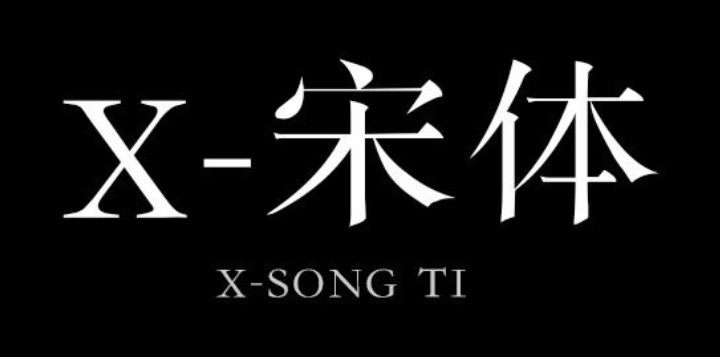
明代有了线装书和宋体字
本次展出的古籍以天一阁所藏明代书籍为主,同时有华东师范大学图书馆及复旦大学陈正宏教授所藏日本、朝鲜半岛、越南、法国等国家和地区的书籍,充分展现了明代书籍的特殊魅力及其在世界范围内产生的深远影响。
天一阁所藏明代书籍久负盛名。明代书籍文化最突出的贡献表现在书的装帧和刻印方面。在书籍装帧上出现了更加便利的线装,在雕版印刷技术上发明了便于刊刻而又不失美观的宋体字,两者最终成为传统书籍装帧和印刷的规范。
宋体字为何会横细竖粗?
宋体字不仅使用于中国书籍,同样通行于日本、朝鲜半岛、越南等国家和地区,此次展出的朝鲜活字印本《寿斋遗稿》,其使用的宋体字就是根据明刻本宋体字铸造的金属活字。此外,19世纪的法文本《中国图识》,书中插注的汉字书名《大学》《中庸》《论语》以及书后所附中国朝代表中的汉字注释均为宋体字,充分说明宋体字在世界范围内产生的影响力。
宋体字不是宋代的字体,而是明代中期刻书中模仿宋代浙江刻本而形成的一种新字体。宋体字出现之前的印本字体都是手书的楷体,宋体字出现之后,中国古籍印本的字体有了楷体和宋体分庭抗礼的情况。展览的第二部分就是围绕“宋体字”来展示书籍字体的发展史,着重展示了从明代中期至今宋体字的演变过程。
古籍的书板,通常是沿着树干的纵向开切的。文字中的“横划”与木材纤维同一方向,比较好刻,于是刻工就刻得细一点;而文字的“竖画”与木材纤维成直角方向,比较容易刻断,于是刻工就刻得粗一点,这就是宋体字“横细竖粗”这一特点形成的主要原因。此次展出的明范钦天一阁刻本《司马温公稽古录》及其书板尤为珍贵,观众可以近距离欣赏到古代刻工的雕刻工艺。